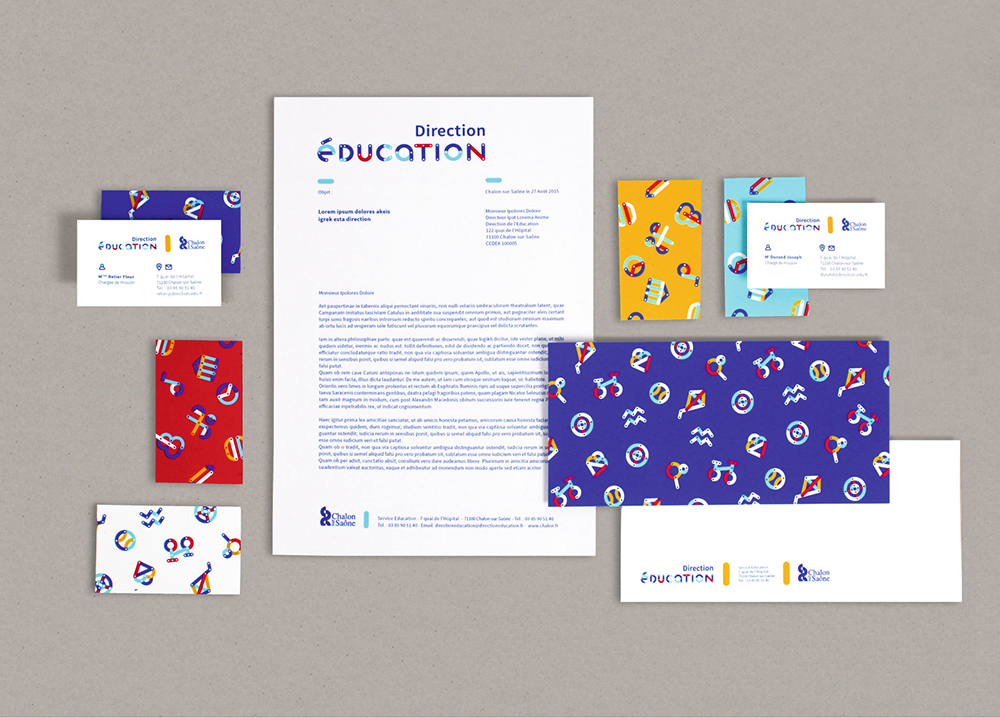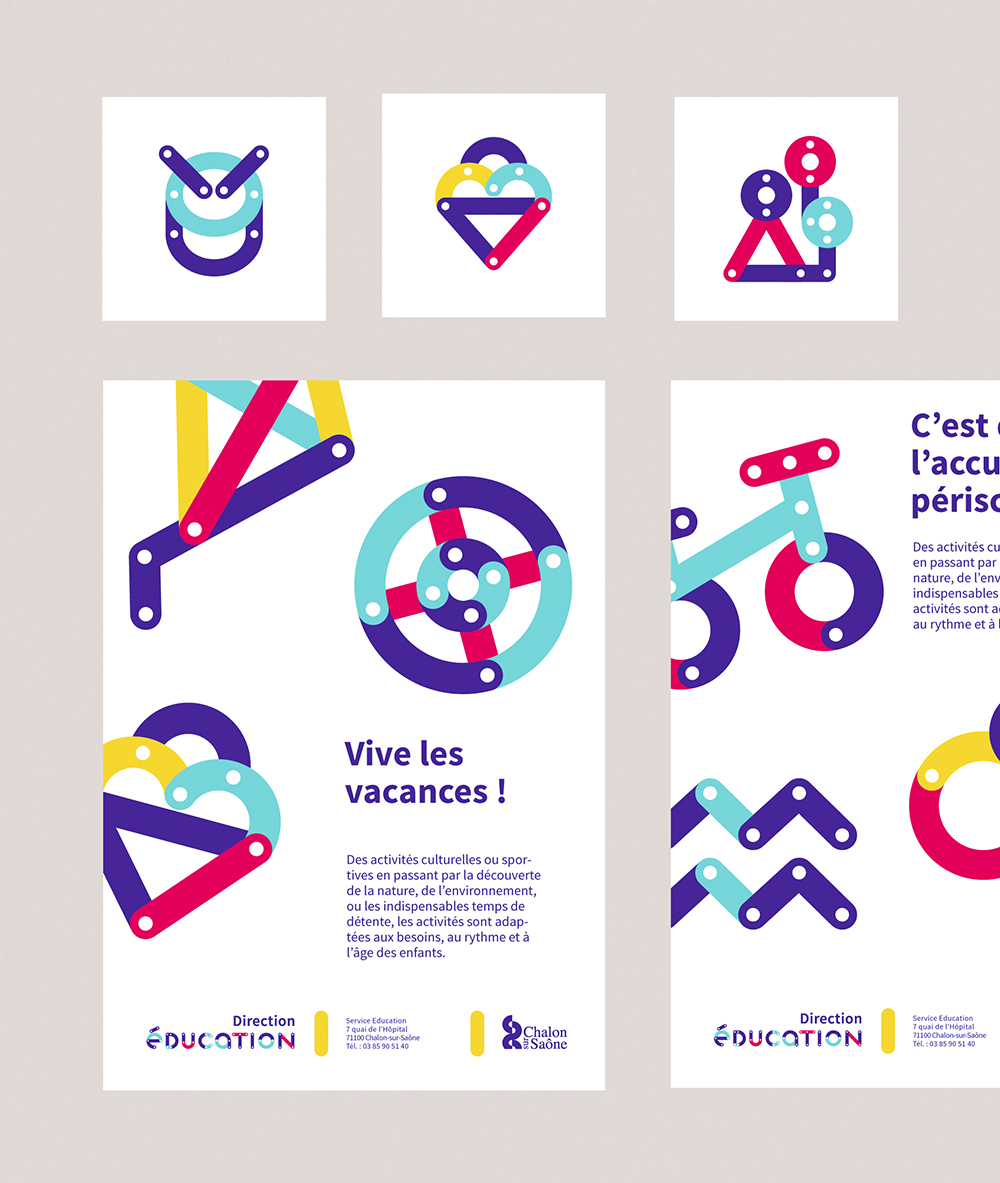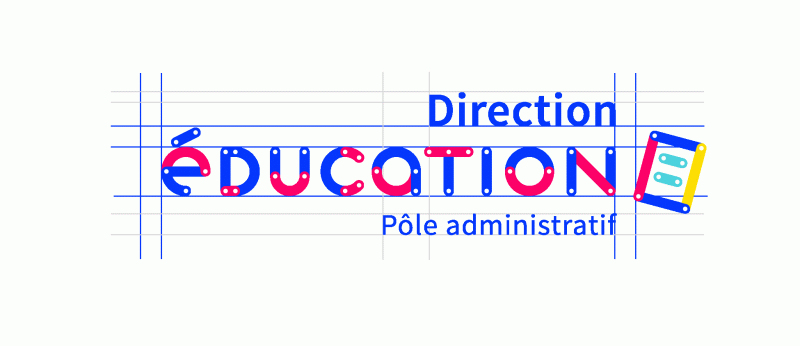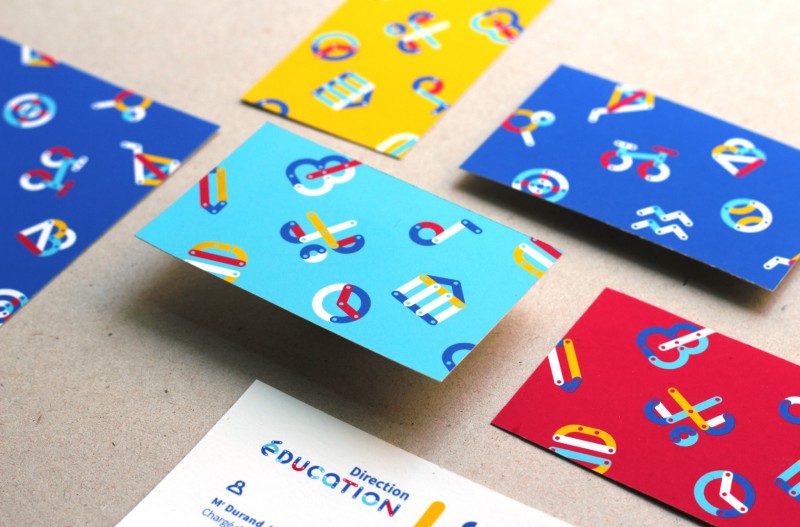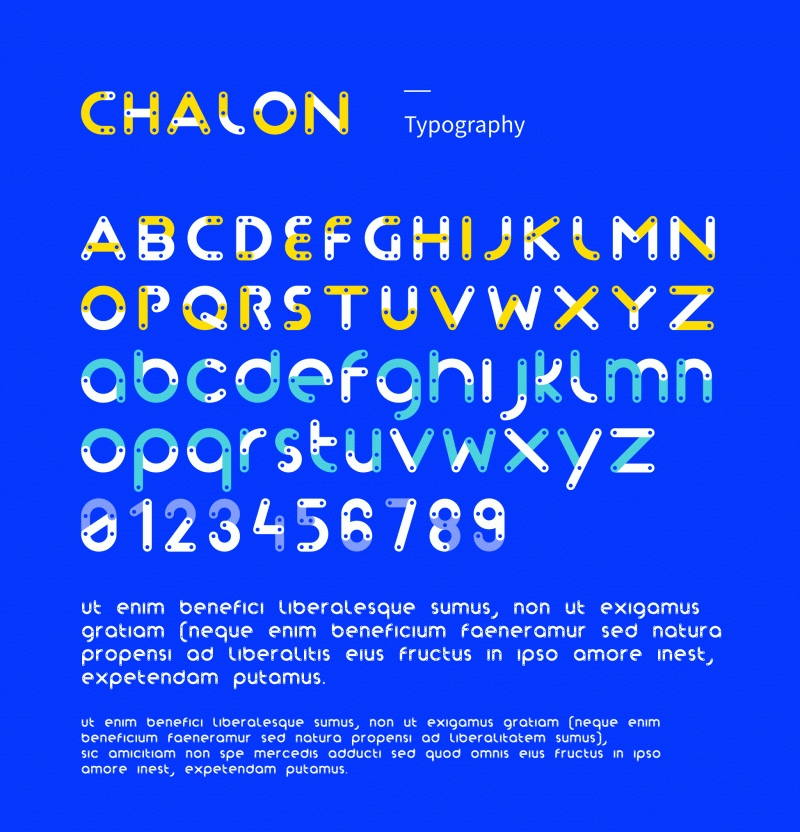
그라핀 교육 브랜드 디자인 : 내 맘대로 뚝딱뚝딱
프랑스 디자인 에이전시 그라핀은 샬롱쉬르손 교육부의 커뮤니케이션 디자인을 조율하라는 의뢰를 받아 로고와 픽토그램, 일러스트레이션과 전용 서체가 모두 포함된 재미있고 발랄한 툴킷을 만들었다.
“사실 이 타입페이스는 두 가지의 서로 다른 문자 집합으로 구성되어 있죠.” 에이전시가 설명한다. “이 두 가지가 서로 겹쳐지면 다양한 색상의 메시지를 만들 수 있어요. 대문자와 소문자의 믹스 앤 매치도 가능하고요.”
학교의 새로운 비주얼 툴킷은 못 모양으로 이어진 색색의 픽토그램들로 조립 완구의 느낌을 갖게 되었다. “조합식 시스템 덕분에 이 프로젝트 전체를 디자인하며 정말 재미있고 즐거웠습니다. 타이포그래피는 여전히 퍼즐같이 어렵지만, 우리는 정말로 디자인하는 과정을 즐겼어요.”